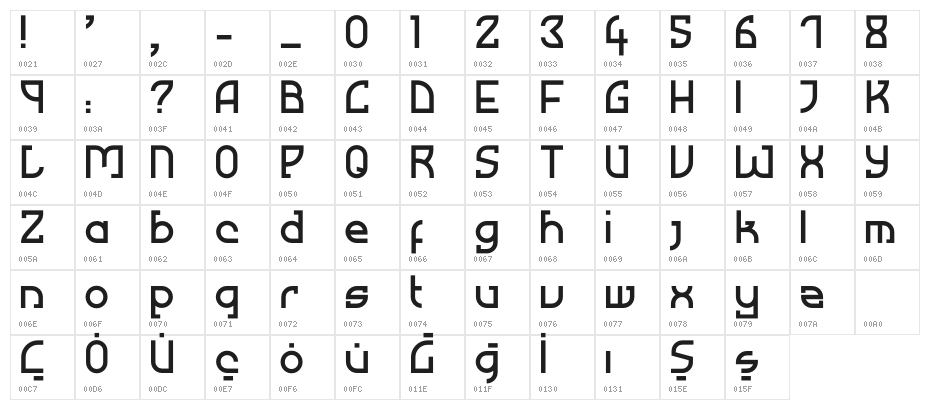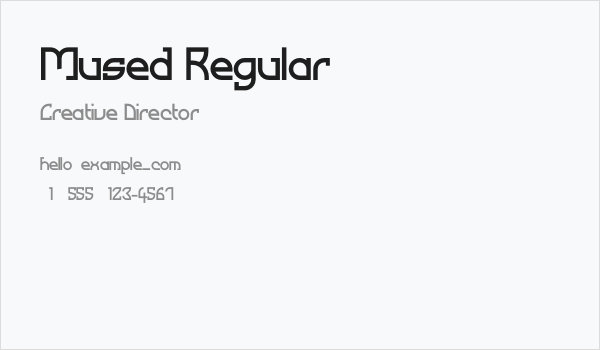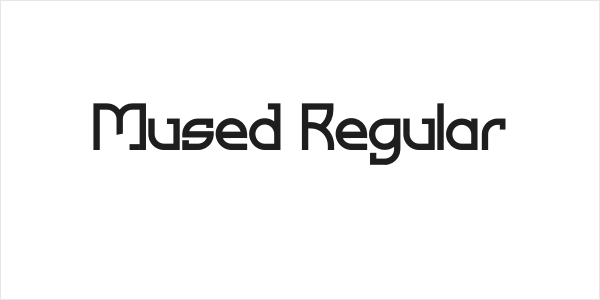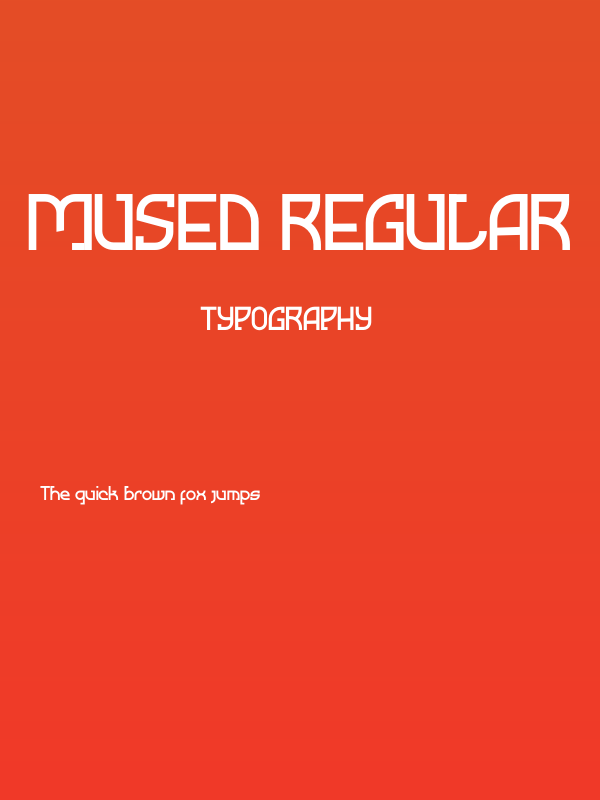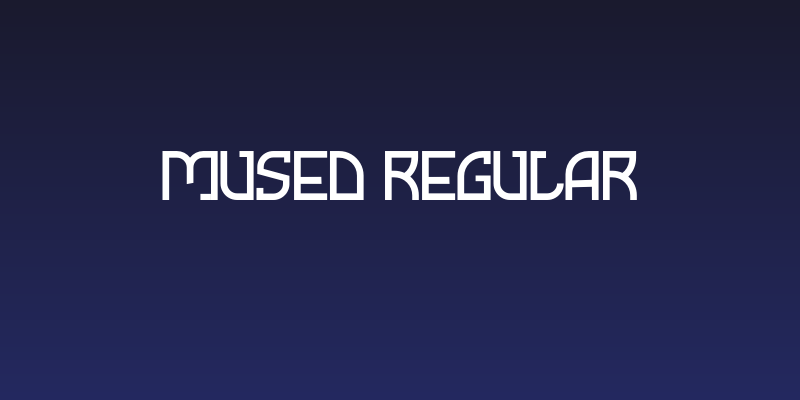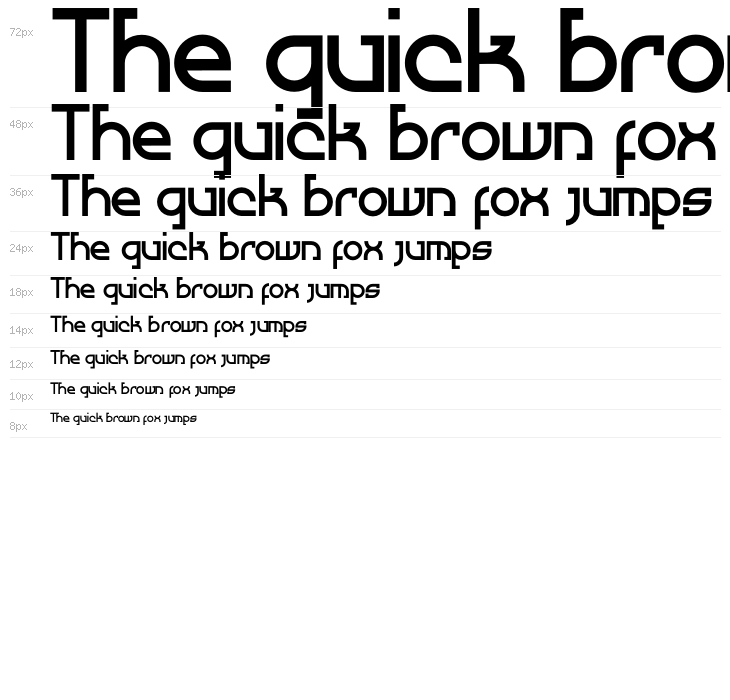
Mused Regular Font
| Gesamtstil | Modern, Geometric |
| Vorgeschlagene Projekte | Ideal for branding, advertising, posters, and digital media projects that require a modern and distinctive look. |